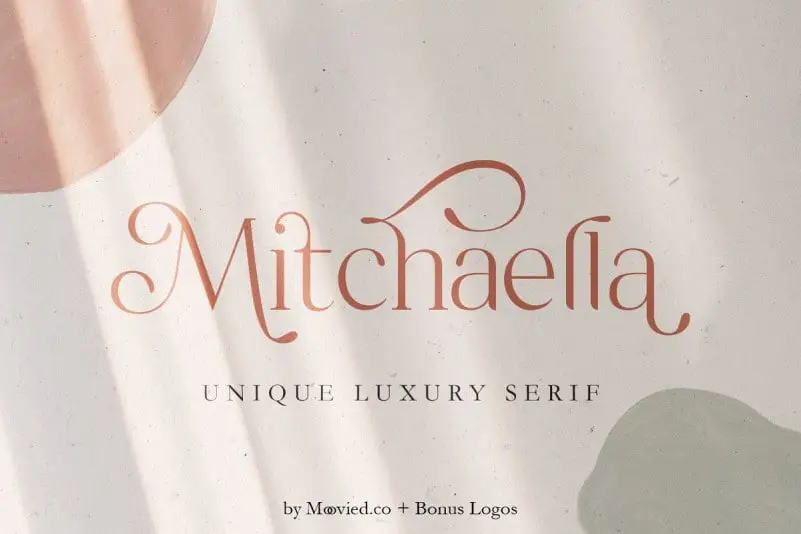
Mitchaella Luxury Serif Font – Download Grátis
Mitchaella Luxury Serif é uma nova fonte serif inspirada no passado antigo, mas que ainda mantém aparência moderna vibrante. Foi criada pelo designer Moovied Co., uma combinação de elegância e contemporaneidade. Esta tipografia serif única e luxuosa oferece muitos caracteres alternativos, ornamentos e suporte para múltiplas línguas, sem esquecer das ligaturas que tornam a escrita mais fluida. Adaptada à geração moderna, Mitchaella Luxury Serif é uma escolha ideal para aqueles que valorizam elegância clássica com um toque de sofisticação contemporânea. Sujeitando-se ao design e estilo deste font, você pode transformar qualquer projeto em algo singular e impecável.